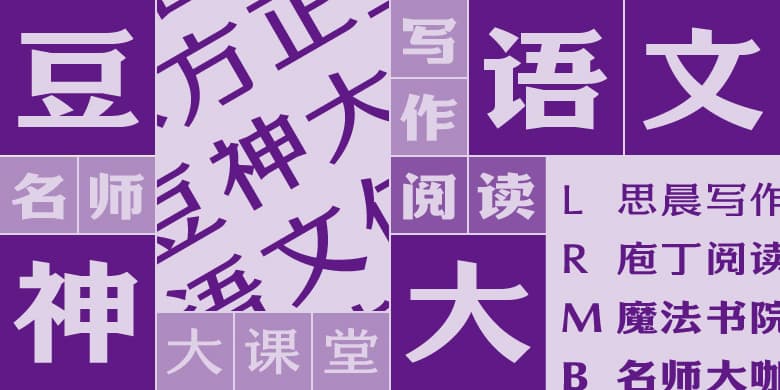
方正豆神大语文体家族
方正豆神大语文体是为豆神教育科技(北京)股份有限公司旗下品牌“豆神大语文”而设计的定制字体。本字体以豆神大语文logo为字体创作基础,经过取舍优化延展设计成全套字库。其字形扁方、重心平稳,体现教育企业给人的亲和与信任感。中文笔形略带宋意,笔画间渗透着中华传统文化的传承,正与中华传统学科——语文的特性相契合。横画尾部向上翘起,象征企业长远发展,同时也表达对万千学子蒸蒸日上的美好祝愿。豆神大语文体共有4个字重,可以适应标题、文本等不同的使用需求。西文与中文匹配设计,字形偏扁,采用半衬线形式,笔画末端弧度与中文相呼应。力求在保持拉丁文书写逻辑的基础上,视觉上与中文相统一。